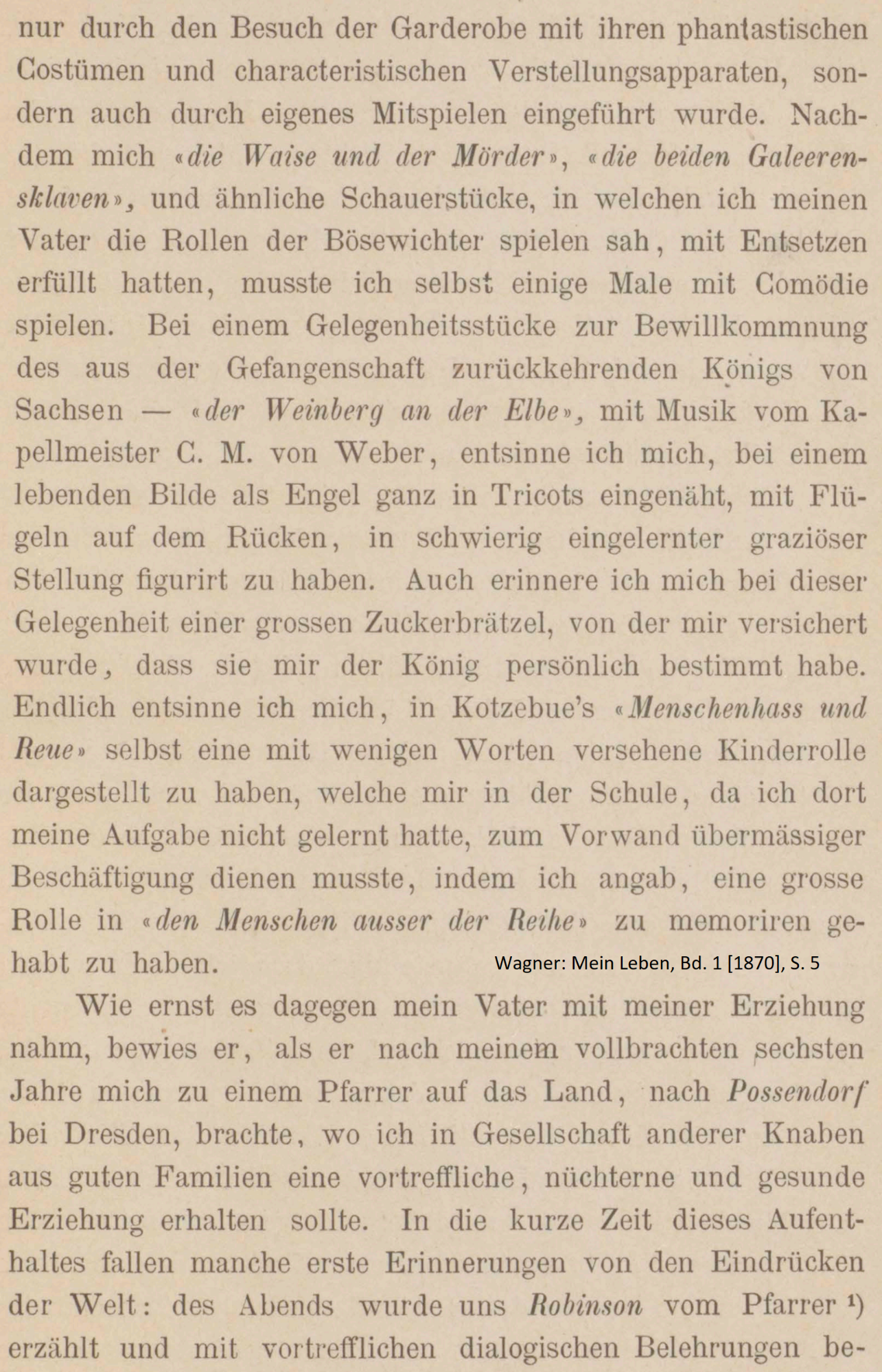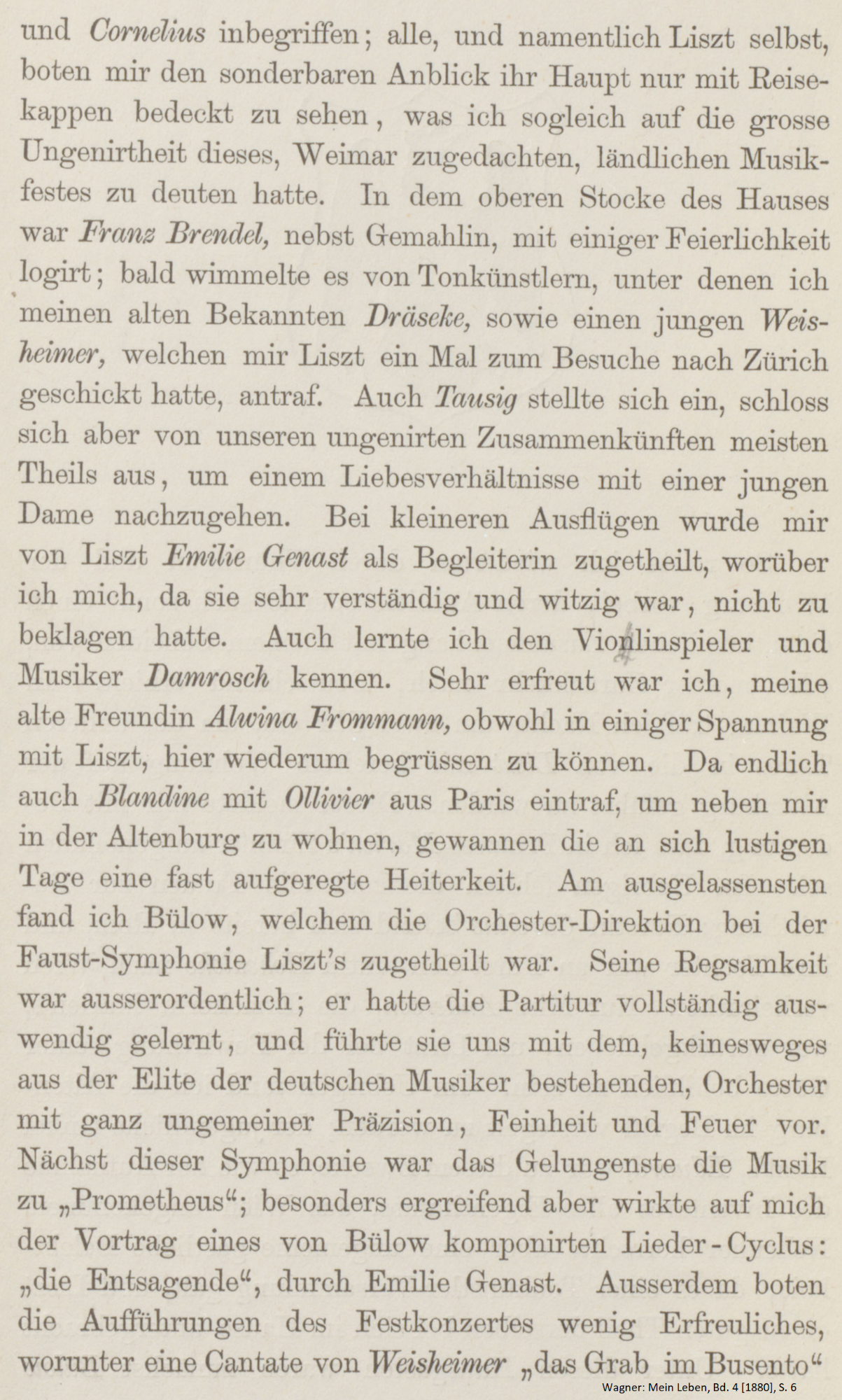
Schrift(en) in Richard Wagners Autobiographie (1870-1880)
Ich beschäftige mich aktuell mit Richard Wagners Autobiographie Mein Leben, die als Privatdruck in 18 Exemplaren hergestellt wurde. Es sind vier Bände, von denen die Bde. 1-3 in der Baseler Druckerei von Giovanni Antonio Bonfantini hergestellt wurden (von der ungewöhnlichen Wahl einer italienischsprachigen Kunstdruckerei erhoffte Wagner sich Diskretion, denn von dem ganzen Vorhaben sollte nichts an die Öffentlichkeit dringen). Band 1 wurde 1870, Band 2 1871 und Band 3 1874 fertiggestellt.
Den vierten Band ließ Wagner dann im Jahr 1880 (aus pragmatischen Gründen) in der Bayreuther Druckerei von Theodor Burger drucken. In einer brieflichen Druckanweisung bittet Wagner, "Typen, Druck u. Papier genau nach dem Muster [der Bände 1-3]" auszuwählen. Allerdings gab es dabei wohl Probleme, denn in einem folgenden Brief an einen Assistenten schreibt Wagner: "Das Anschaffen neuer Typen ängstigt mich, weil Verzögerung fürchtend! [...] hat er keine à peuprès-ähnlichen Typen?"
Jetzt also meine Frage(n) an Euch: Für mich als Laien ist nicht eindeutig zu erkennen, ob der Bayreuther Druck von 1880 identische Typen wie der Baseler Druck von 1870 verwendet (siehe beigefügte Schriftproben). Wie seht Ihr das? Könnt Ihr diese Typen identifizieren? Was meint Wagner mit "à peuprès-ähnlichen Typen"? Ist das ein fachlicher Terminus oder soll das einfach heißen, dass die Schrift möglichst gleich ausschauen soll?
Es sind auf jeden Fall unterschiedliche Schriften (Vergleich z.B. B, E, a, r, ...) aber mit gewissen Ähnlichkeiten bzw. aus einer Gattung. Um welche es sich handelt kann ich dir nicht sagen.
Zu der Zeit hatten Schriften in der Regel keine Namen wie sie heute üblich sind sondern wurden bestenfalls nach Schriftstil und einer Nummer benannt (z.B. Antiqua Nr. 28 oder Placat-Schrift Nr. 33). Auch war der Markt von vielen kleinen Schriftgießereien geprägt und es ist unwahrscheinlich, dass in Bayreuth die selben Schriften verfügbar waren wie im 500 km entfernten Basel. Unmöglich ist es natürlich nicht. Beim Papier dürfte es sich ähnlich verhalten haben.